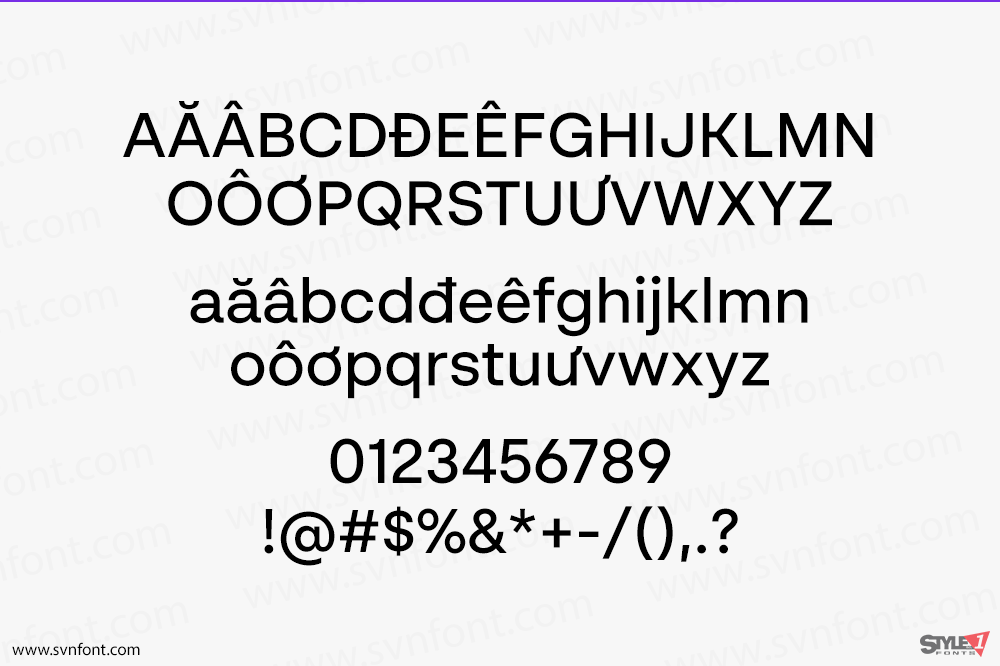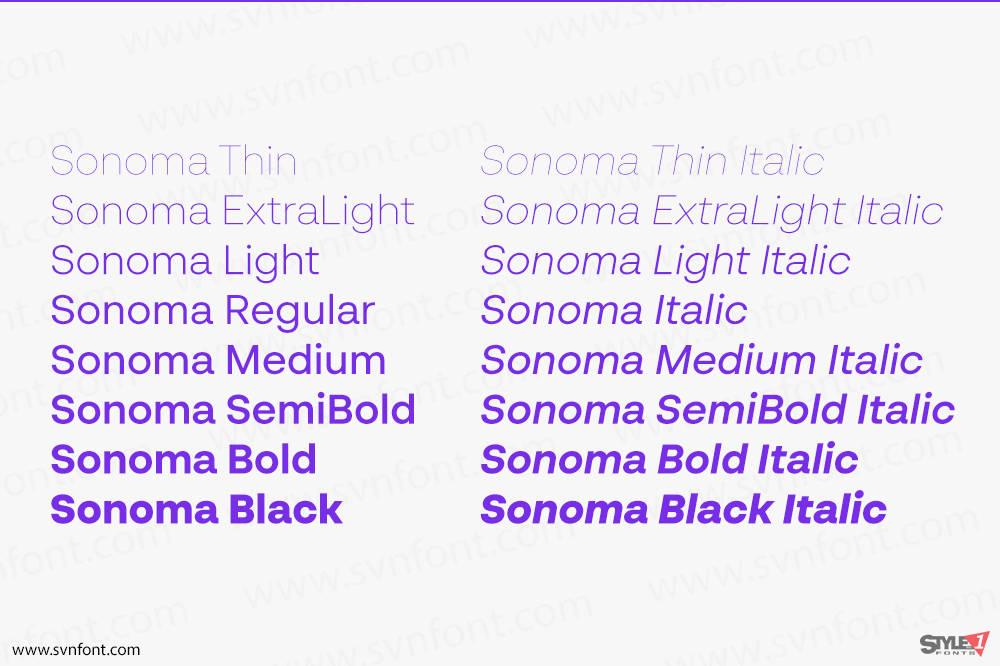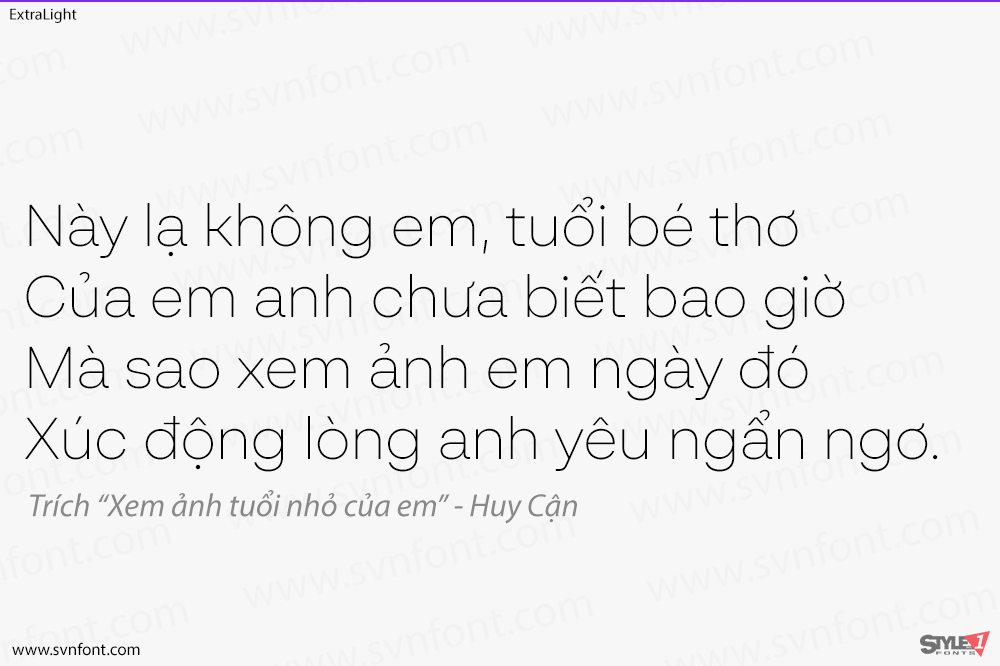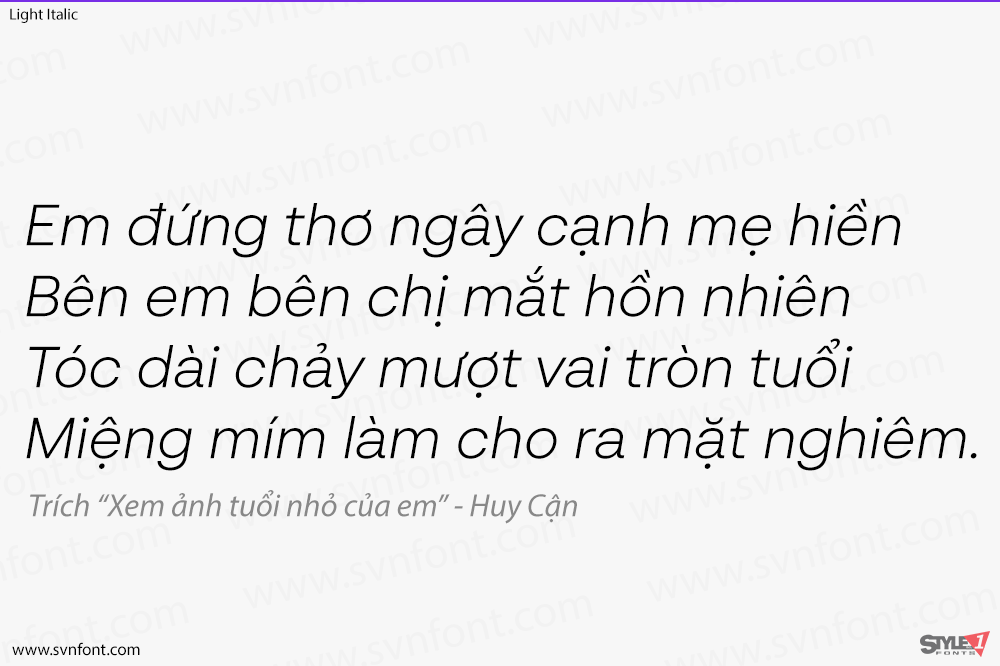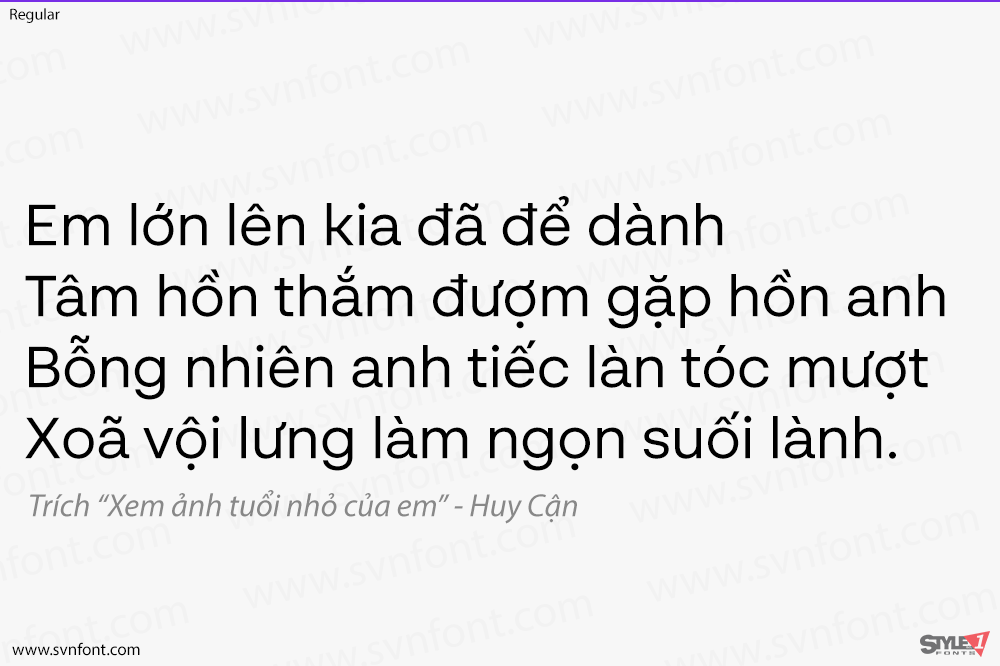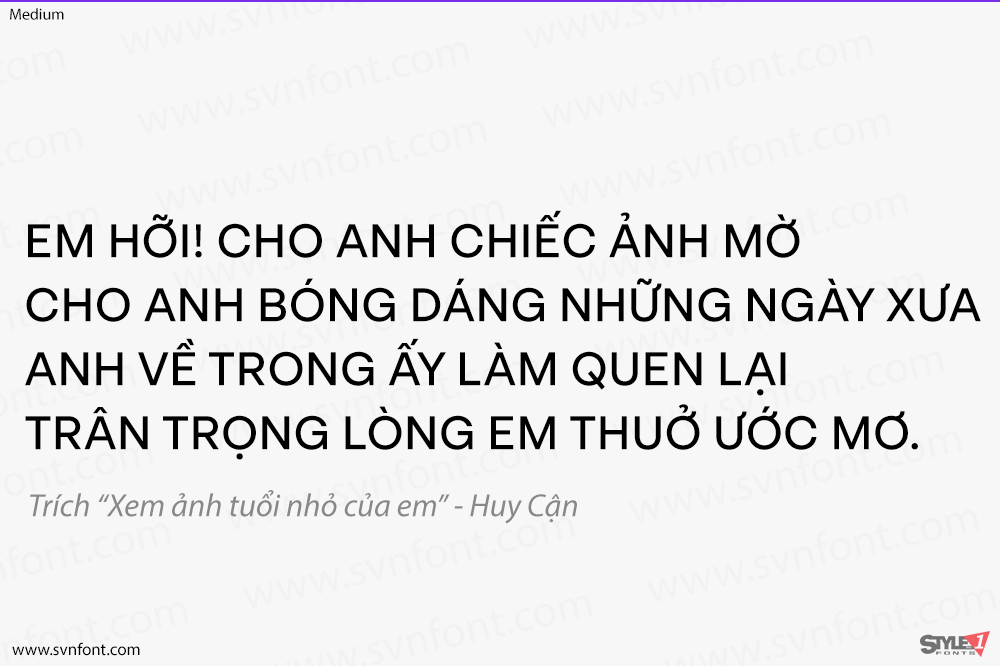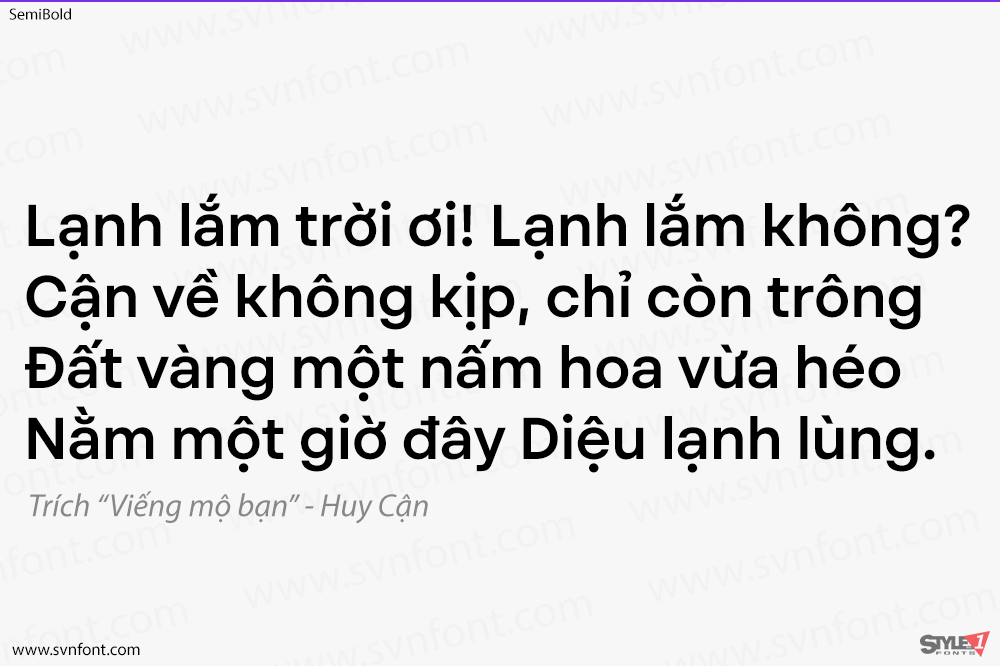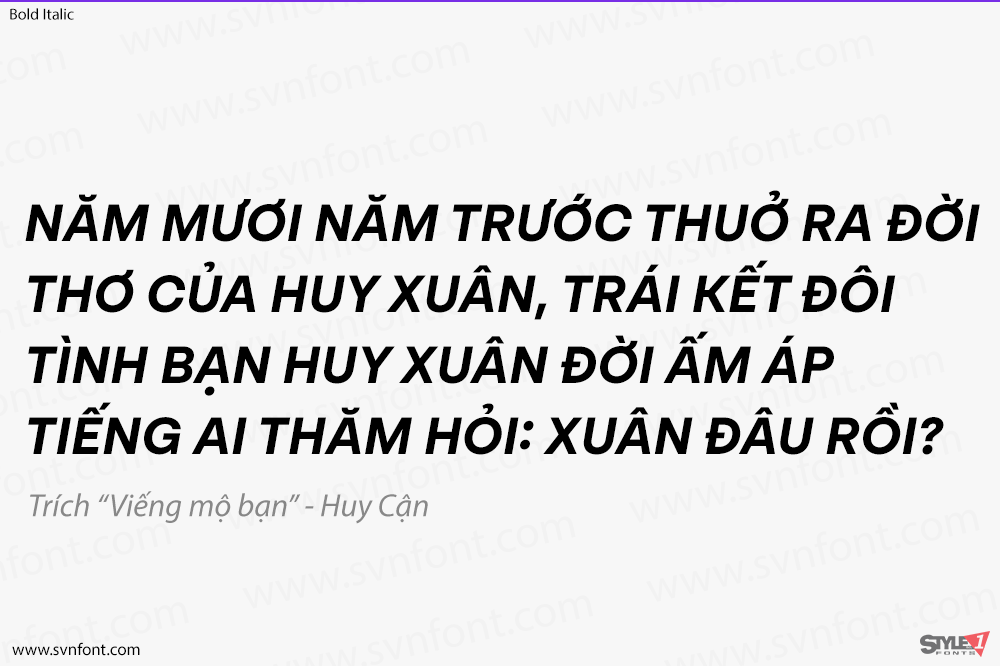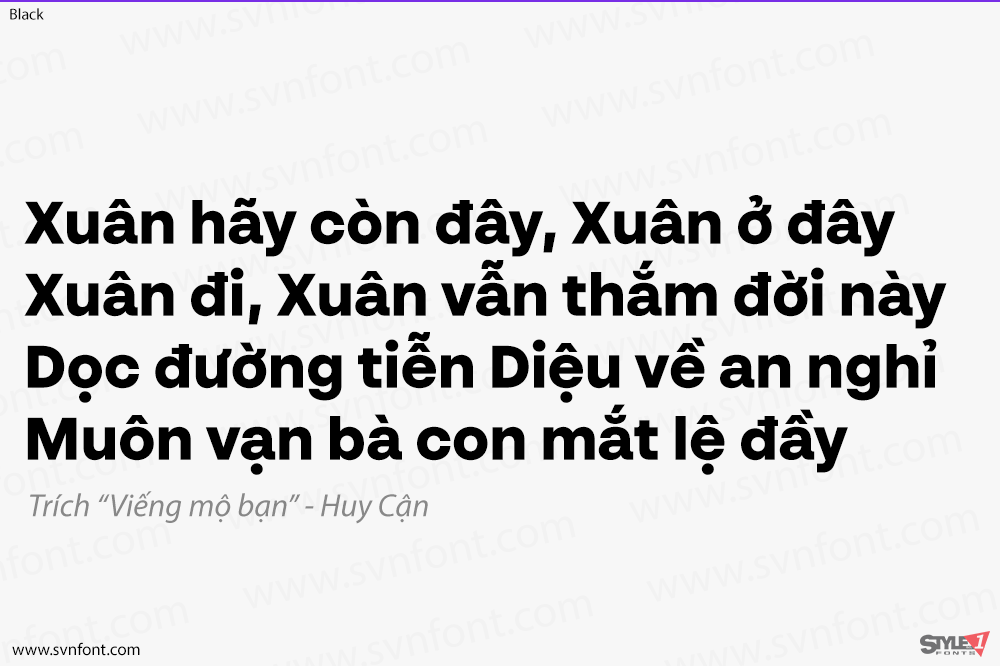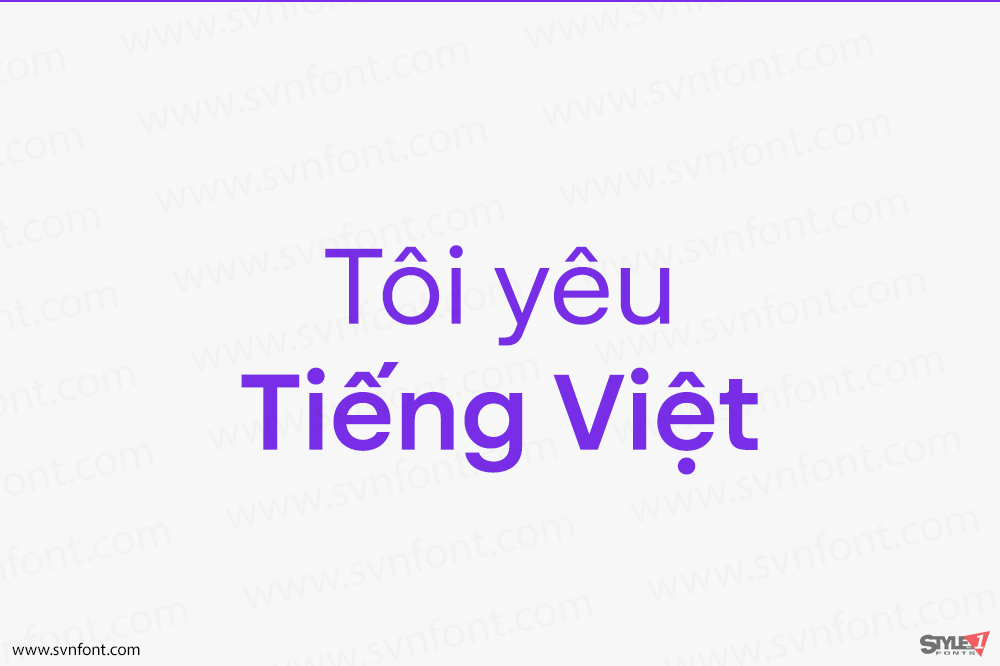
BR Sonoma là một kiểu chữ grotesque hình học mới được xây dựng cho thế kỷ 21 với thẩm mỹ hiện đại được tinh chỉnh. BR Sonoma dựa trên nền tảng được đặt ra bởi các kiểu chữ grotesque Thụy Sĩ cổ điển như Helvetica và Univers nhưng kết hợp các đặc điểm của chúng với một cơ sở hình học mạnh mẽ hơn thường thấy trong các tác phẩm kinh điển ban đầu khác như Avant Garde, Futura và Avenir. Sự kết hợp lai giữa phong cách hình học và tân-grotesque này tạo ra một bản thể hiện đương đại của thể loại sans-serif đa năng, được đặt nền móng vững chắc trong sự hiện đại, đơn giản và chức năng.
BR Sonoma có sẵn trong 16 kiểu dáng được chế tác tinh xảo, với tám độ đậm nhạt từ Thin đến Black. Các font chữ cũng cung cấp hỗ trợ kiểu chữ nâng cao với các tính năng OpenType như các dạng chữ nhạy cảm với chữ hoa/thường (case sensitive forms), biểu tượng (icons), kiểu chữ thay thế (stylistic alternates), số không gạch chéo (slashed zeros) và nhiều bộ chữ số khác nhau (multiple figure sets). Đồng thời cũng chứa hỗ trợ ngôn ngữ nâng cao theo tiêu chuẩn.
Nhà thiết kế: Christoph York
Nhà phát hành: Brink